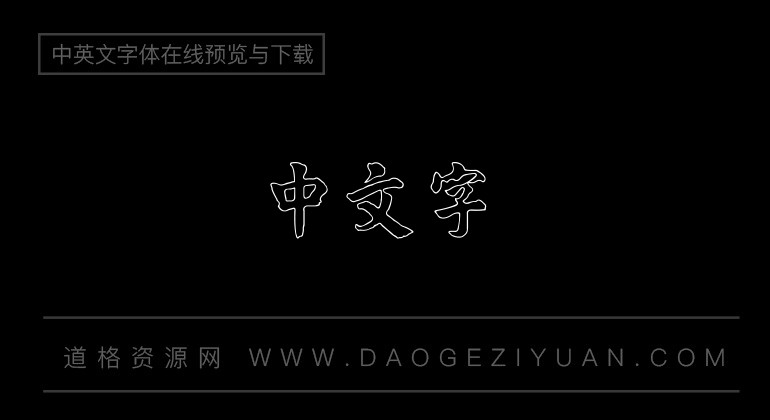
金梅楷书字形空心字体,又称“空心金梅楷书字体”,是一种经典的汉字字体,它的特色是字体的毛笔笔画细腻,线条流畅,字体的格式简洁而美观。金梅楷书字形空心字体的笔画细腻精细,线条流畅,字体的格式简洁而美观,让人一看就能够感受到它的优雅,它被广泛用于各类文字设计中,是一款非常受欢迎的字体。文件名:jmkaishukongxinfan-1.ttf
金梅楷书字形空心是一款非常不错的手写艺术字体,具有很好的视觉感,适合于文化类的宣传设计、商业类品牌的广告和产品包装设计以及个性化文字排版等较多场景。